标点和符号
标点和其他印刷使用的符号都有他们自己的与字母的发展独立分开的历史。但是你会发现相同的设计流程仍然可以应用,包括重用和适配组件元素和迭代地测试你的设计选择。
简单标点字形
在设计标点时首先要做的事创造“.”符号,也就是句号或句点。
这个字形的形状经常来自于“i”上面的点,有时也被称作头部。在你复制这个点之后,你可能希望让它变得大一点,在打印文本或者屏幕上测试几种不同的尺寸是合适的。
一旦你建立了让你觉得快乐的尺寸,这个点会被作为多种其他标点的基础,包括这些字形:; : ? ! ¡ ¿ · …
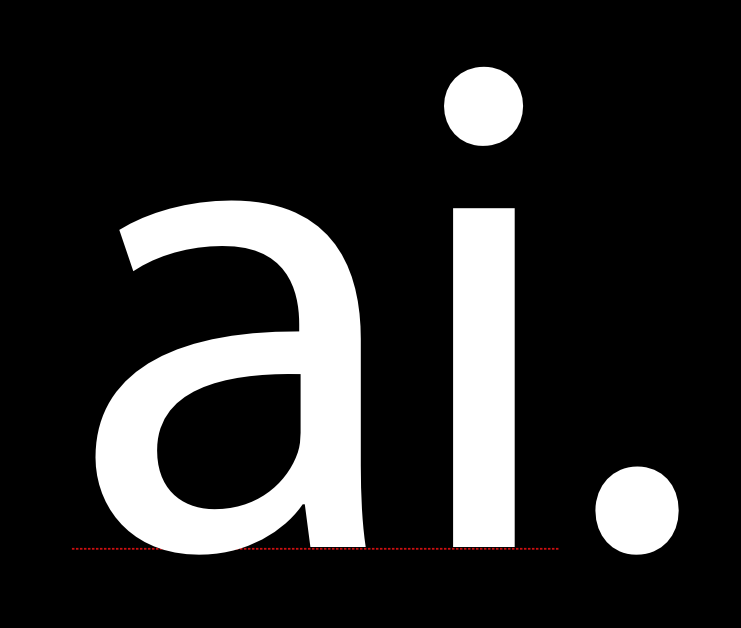
下一个要制作的字形是逗号。逗号的形状可以变化到让你觉得吃惊的程度。在你设计自己的逗号前看一下各种各样的逗号设计是有价值的。
下面的图片展示了逗号可能使用的两种最常用的形式。
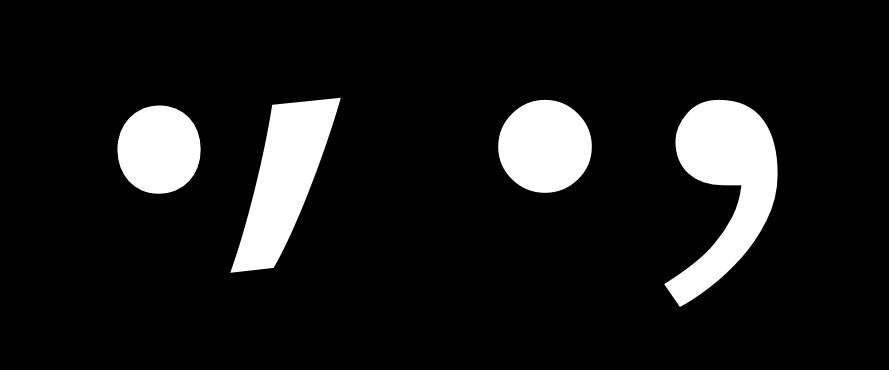
逗号的上部通常比句号小一点点,因为如果一样大小的话看起来太重。在同一张图片上的右边的逗号是应用这种补偿的例子。设计这个字形需要注意的另一种错误是做的太短。
当你有了自己的逗号时,制作分号(;)是非常容易的。
叹号和问号
叹号可能让你产生看起来容易制作的错觉。如果你看了一些字体样式,你会距的优势设计真的是相当简单。
但是这是一个有令人吃惊的机会总数可以表达设计的字形。即使在对比非常小的字体中,点上面的条形经常上大下小。叹号的形式经常与逗号的设计有着某种程度的联系。
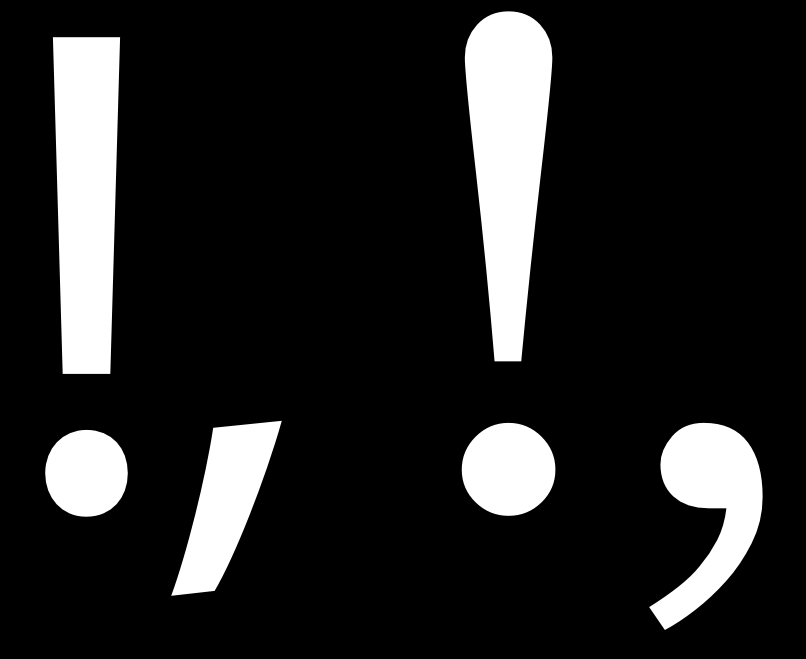
问号也非常难制作,因为它需要你平衡点上面的开放曲线。
设计叹号时可取的方法是在为你的设计选择一个方案之前看甚至测试一些不同的方案。
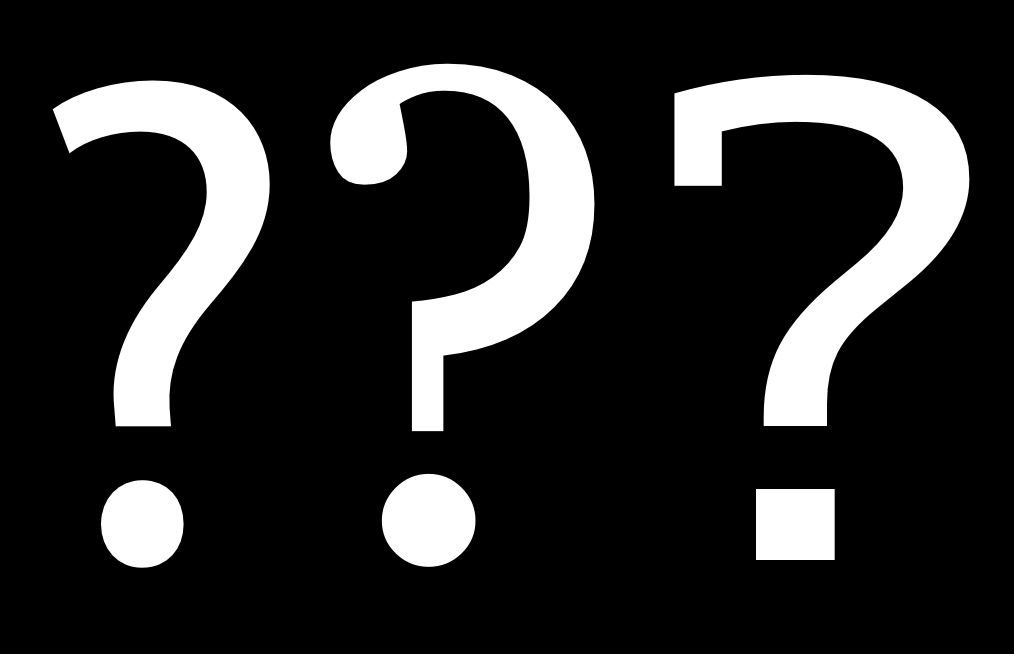
字形 c、C、G、s 和 s 可能提供了设计这个字形的基础,但是你也可以选择一个不同的形式。
额外的符号
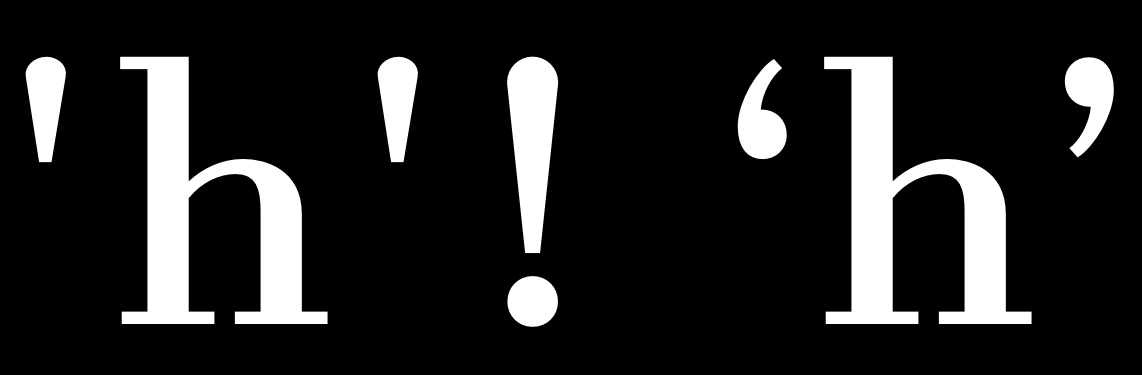
简单的或者竖直的引号–‘和"–与印刷上的引号‘ ’和“ ” ‚ „不同。
通常印刷上的引号与逗号非常接近,但是他们应该比逗号更长,并且经常更弯。
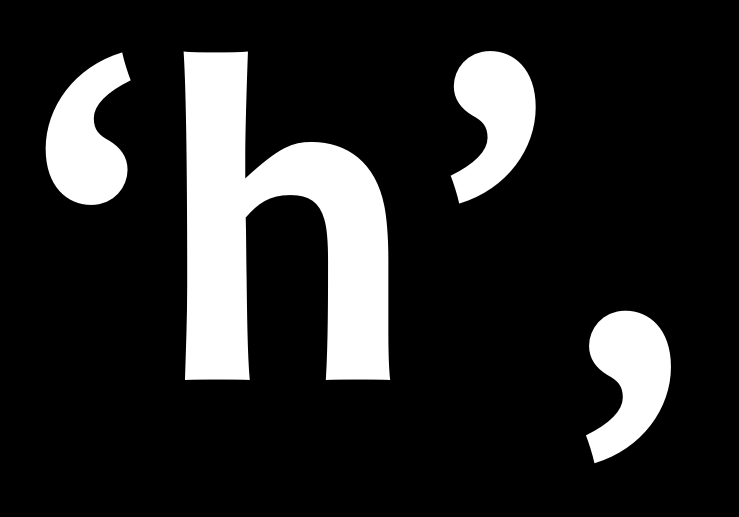
方括号[ ]制作起来相对简单,因为他们在形状上四四方方。不过他们的设计应该反映出你在其余字体样式上所作出的选择。
选择的主要问题是他们应该多高多深。约定是他们的高度应该轻微地超过大写字母的,并且底部比基线低约小写字母底深的 3/4。
这些选择也会反映到圆括号()和花括号{}中。这三个符号的茎应该比大写和小写字母的茎的细。
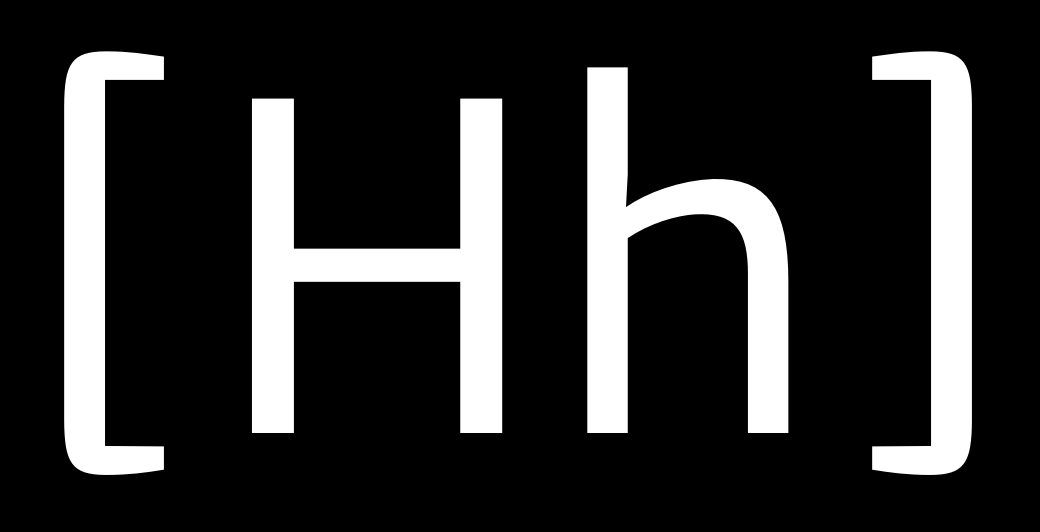
圆括号应该在有关形状设计的基础上绘制,比如 D、C 和 G。
花括号最明显的是他们的设计可以在非常大的程度上变化。花括号在这一点上与叹号相同。花括号的粗细分布可能类似数字的分布,因为它有时可能违反你在其余的设计中要遵循的规则。